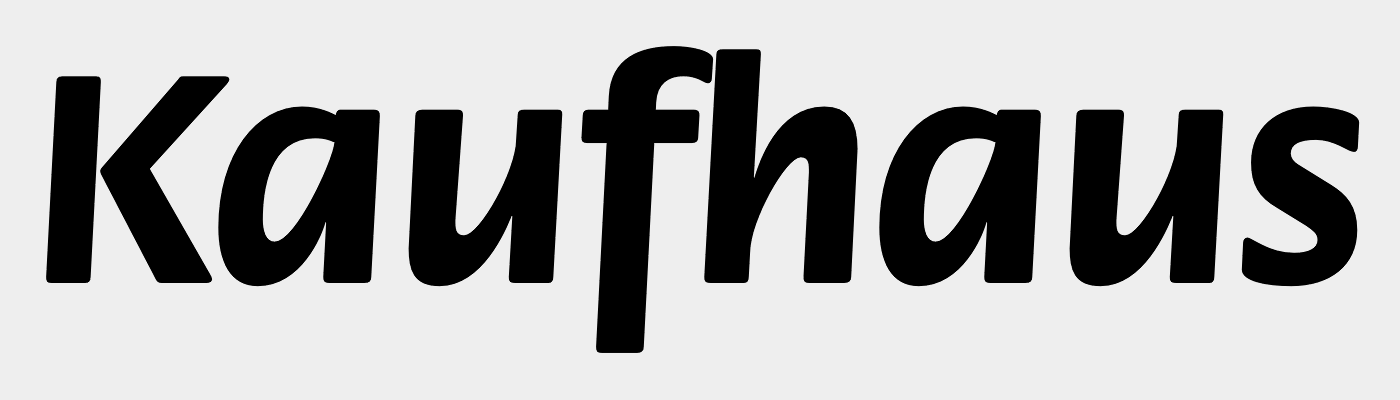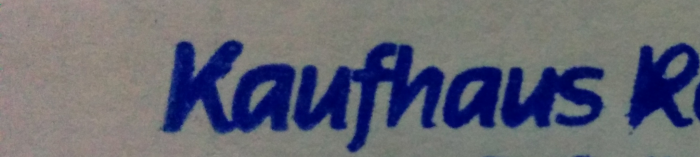
ich hab einen alten Stempel und möchte die Schriftart wieder verwenden,
hab aber kein Plan welche das ist.
Wisst Ihr um welche es sich handelt:
Ich hatte es ja schon mehrfach erwähnt, drum fasse ich das hier mal zusammen.
In der Vor-Computer-Zeit gab es praktisch 5 Bereiche der Schriftennutzung, die mehr oder weniger unabhängig nebeneinander existierten, und zwischen denen es eigentlich nur inspirativen Austausch gab.
Der sicher größte Bereich war hier der Schriftsatz für den Buch- und Akzidenzsatz mit Schriftgießereien in praktisch jeder größeren Stadt, die ihre Schriftentwürfe von den Größen der Branche hatten, aber auch kräftig voneinander abkupferten, wobei "abkupfern" durchaus wörtlich zu nehmen ist, sind einige identische Schriften bei verschiedenen Schriftgießereien doch auch galvanoplastisch kopiert worden. Diese Schriftgießereien fertigten aber zumeist nur Lettern für Druckereien, einige aber auch die Lettern, die dann von Schreibmaschinen-Herstellern auf ihre Typenhebel montiert wurden - aber hier eben speziell gestaltete Monospaced-Schriftarten.
Der 2. Bereich der klassischen Schriftennutzung waren dann die Steinmetze. Diese arbeiteten - und arbeiten bis heute aber oft nach Schriftmusterbüchern, die innerhalb der Werkstatt über Generationen einen gehüteten Schatz darstellen. Diese Schriftvorlagen stammen dann oft von Meistern oder in der Schriftgestaltung guten Gesellen der Werkstatt, die sich sicherlich auch von den Moden der Druckschriften leiten ließen, aber eben doch eigene Interpretationen zeichneten, die dann eben auch stilistisch sich nach dem Zweck der Arbeit richteten. Also eher ernst und würdig waren.
Der 3. Bereich sind Maler und Lackierer. Auch hier diktierte wieder das Material und das verwendete Werkzeug den Schriftstil. Wie bei den Steinmetzen wurden auch hier handgezeichnete Schriftvorlagen genutzt, die dann von einem guten Schildermaler an den gewünschten Text frei angepasst wurden, und oft hatten die Werke der lokalen Kollegen mehr Einfluss auf die eigenen Entwürfe, als die gerade modernen Schriften der Druckerkunst, sodass man bei Hausanschriften aus dieser Zeit durchaus für bestimmte Städte einen eigenen, durchgehenden Stil wahrnehmen kann.
Auch bei Fahrzeuganschriften wurde damals noch nach handgezeichneten Entwürfen gearbeitet, und ich hatte zu meiner Lehrzeit noch miterlebt, wie in meinem Ausbildungsbetrieb die Lackierer-Lehrlinge noch die alte Technik erlernten:
Da hatte der "Lehrling" die Beschriftung zunächst sauber auf Transparentpapier gezeichnet, wobei er eben das Schriftmuster "Druckschrift" aus dem Lehrbuch durchgepaust hatte. Dann wurde auf die lackierte Autotür mit Zuckerwasser eine Stanniolfolie geklebt und fein glatt angerakelt. Mit Malerkrepp wurde darauf die Reinzeichnung fixiert, und mit einem spitzen Griffel in die darunterliegende Zinnfolie übertragen, anschließend wurden dann aus der Stanniolfolie die Buchstaben ausgeschnitten, herausgepult und mit einem feuchten Tuch oder Schwamm die Zuckerreste von der freigelegten Lackfläche entfernt.Durch diese Schablone konnte dann lackiert werden.
Der 4. Bereich waren dann die Kalligrafen und die freihändig arbeiteten Schildermaler, die natürlich überhaupt keine Vorlagen brauchten, waren diese praktisch selbst auch Schriftgestalter.
Und letztlich der 5. Bereich waren die Stempelhersteller, die mit ihrem Material- und Werkzeugbedarf wieder ein eigenes Universum bildeten, obgleich sich ihre Methoden in vielem mit dem klassischen Schriftsatz überschnitten.
Auch hier wurde mit Lettern gesetzt, und man nutze praktisch das gleiche Instrumentarium wie der Schriftsetzer, nur dass sie eben Mater-Lettern verwendeten, und ihre Spartien einen Tick höher als die Lettern waren, und ihre Texte seitenrichtig im Satz waren. Der Schriftguss erfolgte dabei in gleicher Weise wie der Schriftguss für den Buchdruck, nur dass in das Gießinstrument dann eben statt der Mater eine Pater eingespannt wurde, die dann wohl galvanoplastisch von der Mater abgeformt worden war. Diese Lettern stammten aber eben nicht von den Druck-Schriftgießereien, sondern die Lieferanten für alle Materialien und Werkzeuge zur Stempelherstellung unterhielten ihre eigenen Gießereien und gossen dort eben auch Schriften, die besonders für die Belange des späteren Stempels - also Lettern aus weichem Gummi - gestaltet waren. Auch hier hat man sich an die Moden der Akzidenzdruck-Lettern angelehnt, aber eben feine Details und dünne Linien vermieden. Zu sehr hat man Moden auch nicht mitgemacht, da der Letternsatz eines Stempelherstellers ja praktisch kaum abnutzte, und daher sehr lange nutzbar sein sollte.
Der fertige Satz für dutzende Stempel, die eben so lange gesammelt werden mussten, bis die ganze Fläche des Satzspiegels gefüllt war, wurde dann mit einem dicht umschließenden Rahmen aus deutlich höheren Blindmaterial ausgeschlossen, dann die Form mit der Gummimasse für das Stempelbild, und darauf eine 2. Schicht aus deutlich weicherem Gummi gegossen, um dann um Ofen aus vulkanisiert zu werden.
Als dann modernere Methoden in die Stempelwerkstätten Einzug hielten, die es auch möglich machten, die bestellten Stempel schneller auszuliefern, da man praktisch auch einzelne Stempel sofort fertigen konnte, wanderte das alte Material sang und klanglos in den Schrott, sowohl bei den Stempelwerkstätten, wie auch bei den Herstellern der benötigten Materialien, und damit eben leider auch die Patritzen der Stempel-Lettern-Gießerei, die dann oft auch nie digitalisiert wurden, konnte man für die neuen Techniken doch direkt auf schon vorhandene Computerfonts zugreifen. Es gibt sogar keine Videos über die alte Stempelherstellungstechnik - oder doch?
Nicht ganz, verschiedene Details sind schon anders, aber sie ist so dicht dran, dass sie zumindest Pate gestanden haben wird.